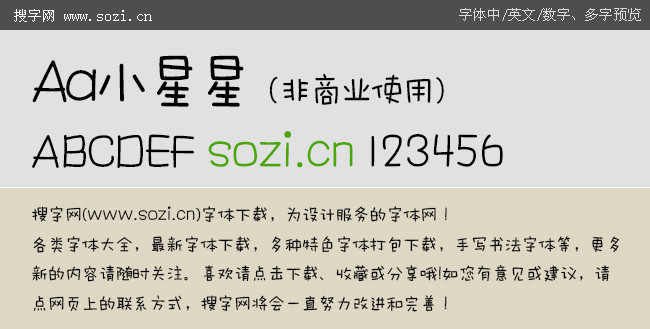
Aa小星星
搜字網(wǎng)給大家提供一款A(yù)a小星星(非商業(yè)使用)中文字體下載,該字體是一款個(gè)性的藝術(shù)字體,字體充滿變化,童趣十足,具有很好的視覺(jué)感,適用于平面宣傳設(shè)計(jì)、網(wǎng)頁(yè)設(shè)計(jì)、海報(bào)設(shè)計(jì)等應(yīng)用(此字體為個(gè)人非商用版,商用可以聯(lián)系QQ:1006760504)。